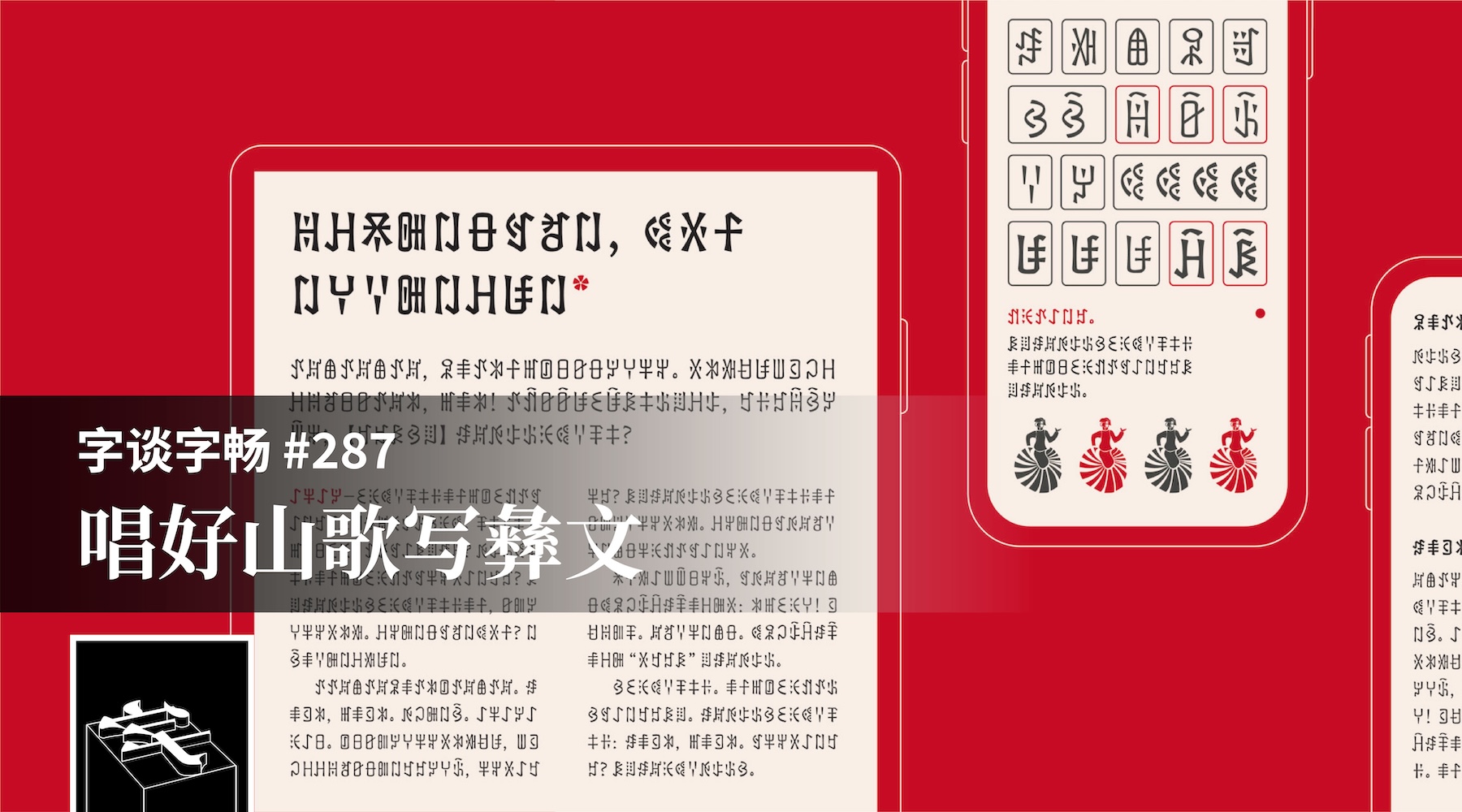
ATypI 2026 Stanford 系列访谈第四期,来到嘉宾席的是演讲者陈月,以及我们的老朋友张可迪。本期节目,两位嘉宾将为我们介绍彝语、彝文的基础知识及发展现状,同时分享各自在彝文字体设计方面的实践及理念。
- 彝文(ꆈꌠꁱꂷ),是彝族用于记录彝语的文字
- 藏缅语族,汉藏语系中除去汉语族以外的语言
- 壮族的名称源于布獞(Bouxcuengh),曾被写作「獞」(zhuàng),后改为「僮族」,1965 年又改「僮」为「壮」
- 改土归流,是指明初到清代中央朝廷废除少数民族的土司、派任流官的制度
- 毕摩(凉山彝语:ꀘꂾ /bi mox),彝族从事原始宗教和文化活动的人
- 奢香夫人,明代彝族土司,政治家;张超作词作曲、凤凰传奇演唱的同名歌曲《奢香夫人》即以此人物为主题而创作
- 《老司机带带我》,以云南彝族音乐为基础而创作的歌曲
- 《小河淌水》,融合大理彝族文化及汉族文化而创作的民歌
- 《金银鸟》,斯琴格日乐等人制作、演绎的彝族民歌
- 《远方的客人请你留下来》,以彝族音乐为基础而创作的普通话歌曲,范禹填词、曲比阿乌演唱
- “From Fragmentation to Belonging: The Development and Standardization of the Yi Script in Southwest China”,陈月在 ATypI 2026 Stanford 的演讲
- 贵州省彝学研究会、贵州省民族事务委员会民族语文办公室、贵州民族学院彝文文献研究所、贵州省毕节地区彝文翻译组(编).《简明彝汉字典》 .贵州民族出版社,1991 年
- 滇川黔桂彝文协作组(编).《滇川黔桂彝文字典》.云南民族出版社,2001 年
- 滇川黔桂彝文协作组、贵州工程应用技术学院彝学研究院、马立三(编).《通用彝文字典》.贵州民族出版社,2016 年
- 《通用彝文规范方案》,贾海霞、沙马拉毅的研究及实践成果
- 阿町字体(Aki),陈月设计的彝文字体,获 TDC 2025 Yound Ones 学生奖
- 悠然隶黑,张丛馀、陈月合作设计的字体,包含彝文字符
- 爨宝子碑,具有重要书法价值,藏于云南省曲靖市爨文化博物馆
- Niepsha Cursive,张可迪制作的凉山规范彝文字体试验项目